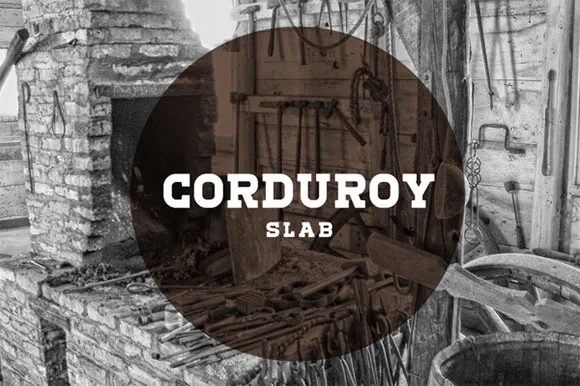
A Corduroy Font é uma elegante escolha para designers que valorizam um estilo sóbrio com toques modernos. Esta slab serif foi criada pelo designer Hamilton, trazendo características fluidas e arredondadas capazes de enriquecer seu trabalho gráfico. Seu design suave se mistura perfeitamente com texturas geométricas ou artesanais, tornando-a um recurso versátil para trabalhos que incluem branding, identidade visual e websites modernos. A Corduroy se presta muito bem a texturas de texto grandes em cabeçalhos e subtítulos, oferecendo uma combinação harmônica entre seriedade e leveza. Com sua designação certeira de Hamilton, esta font é tanto uma aposta segura quanto um elemento diferenciador para seus projetos.